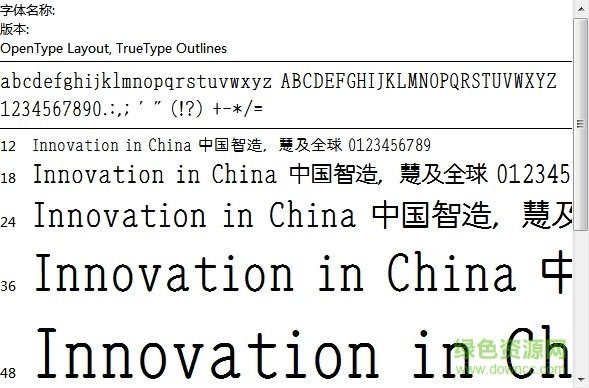
薄樱体是一款适用于系统字体的端正字体,笔画流畅、造型端方,有着容易辨认的外观和结构,让大家的阅读更加舒适和便捷,喜欢的朋友不妨来绿色资源网体验吧!
薄樱字体一笔一画非常端正,字形大方得体,整体效果非常出色,可广泛应用于平面设计、广告设计、报纸杂志、正文标题等领域。
薄樱体可以运用在电脑中来标注严谨图文,也可以当做手机字体,让系统文件更容易被读取,同时也可以为你的平民设计、包装设计带来比较美观的体验。